Lost Time is Never Found Again.
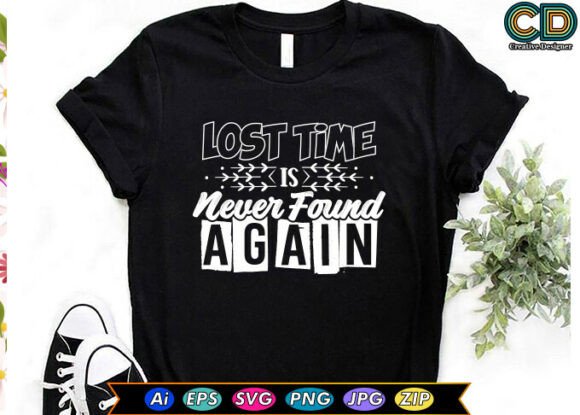
Wenn Sie nach hochwertigen Assets wie Lost Time is Never Found Again. suchen, ist dieses Premium-Paket eine fantastische Wahl für Ihre kreativen Projekte.
Mit Präzision gefertigt, bietet Lost Time is Never Found Again. saubere Vektoren, eine reibungslose Typografie und eine kommerzielle Lizenz für ein beruhigendes Gefühl.
Egal, ob Sie POD-Produkte (Print on Demand), Hochzeitseinladungen oder Social-Media-Grafiken erstellen, Lost Time is Never Found Again. ist die ideale Wahl.